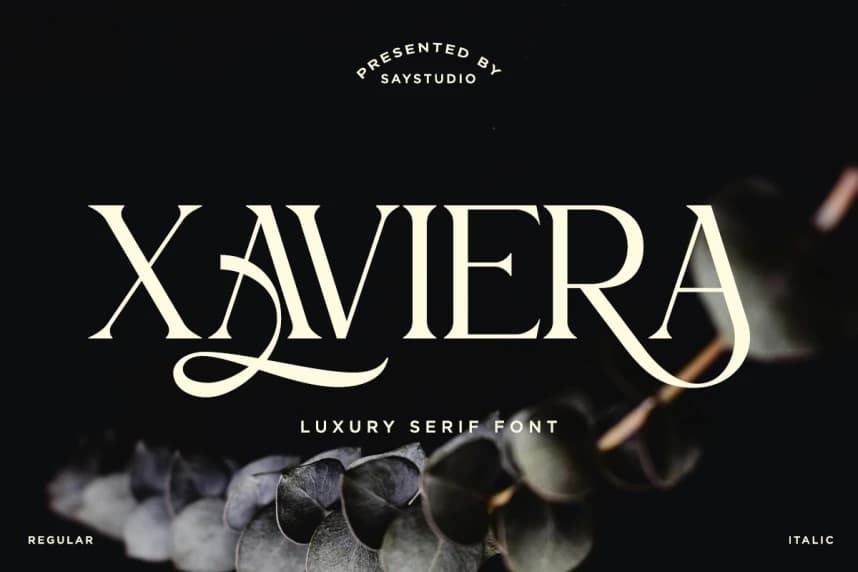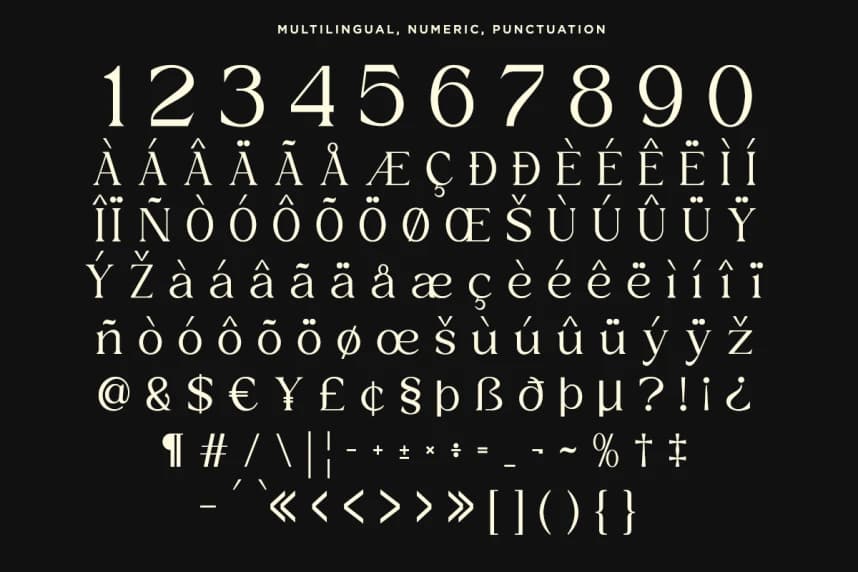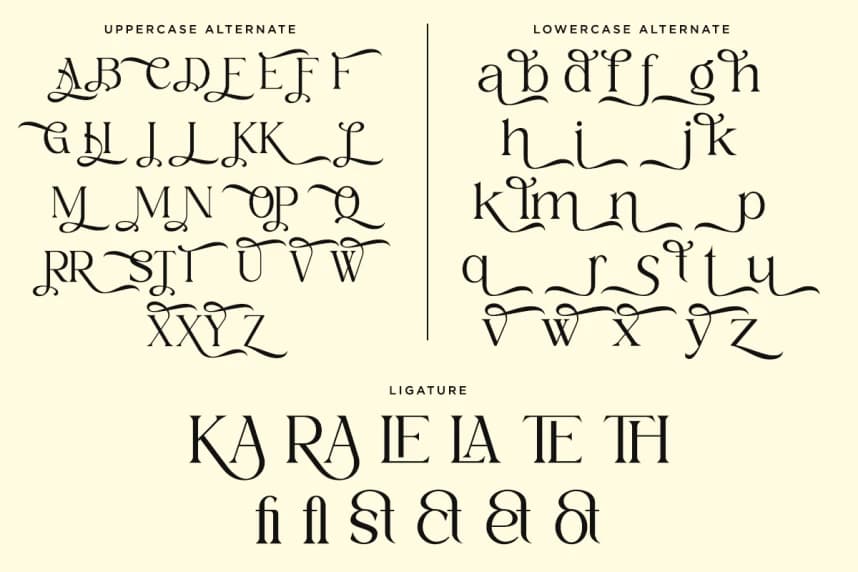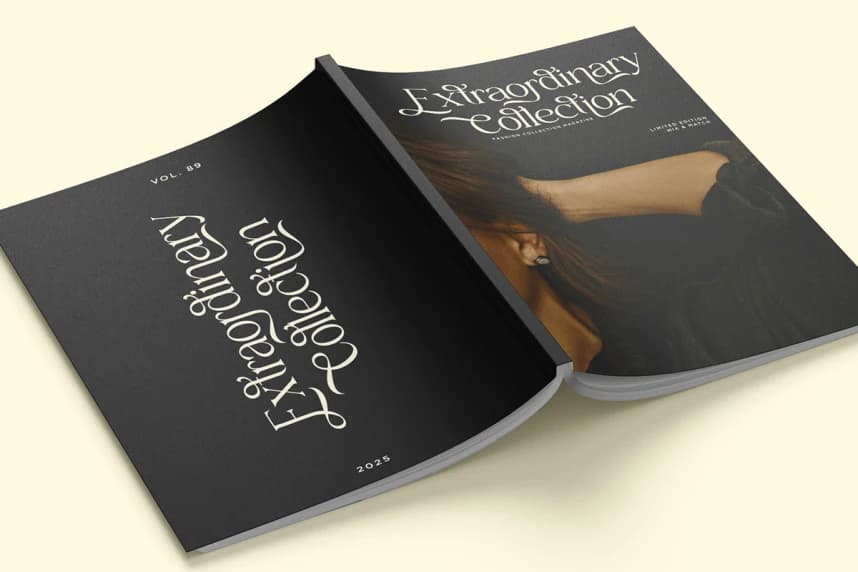
Xaviera DEMO Font – modern zarafet ile zamansız sofistikasyon arasındaki mükemmel uyumu yakalayan bir yazı tipi. Premium markalaşmayı güçlendirmek amacıyla tasarlanan Xaviera, rafine kıvrımlar ve şık ayrıntılar sunar; bu da onu logolar, davetiyeler ve üst düzey pazarlama materyalleri için ideal kıla
Xaviera DEMO Font – modern zarafet ile zamansız şıklığın mükemmel armonisini yakalayan bir yazı tipidir. Premium markalaşmayı güçlendirmek için tasarlandı; Xaviera, rafine kıvrımlar ve şık detaylar sunar, bu da logolar, davetiyeler ve üst düzey pazarlama materyalleri için idealdir.